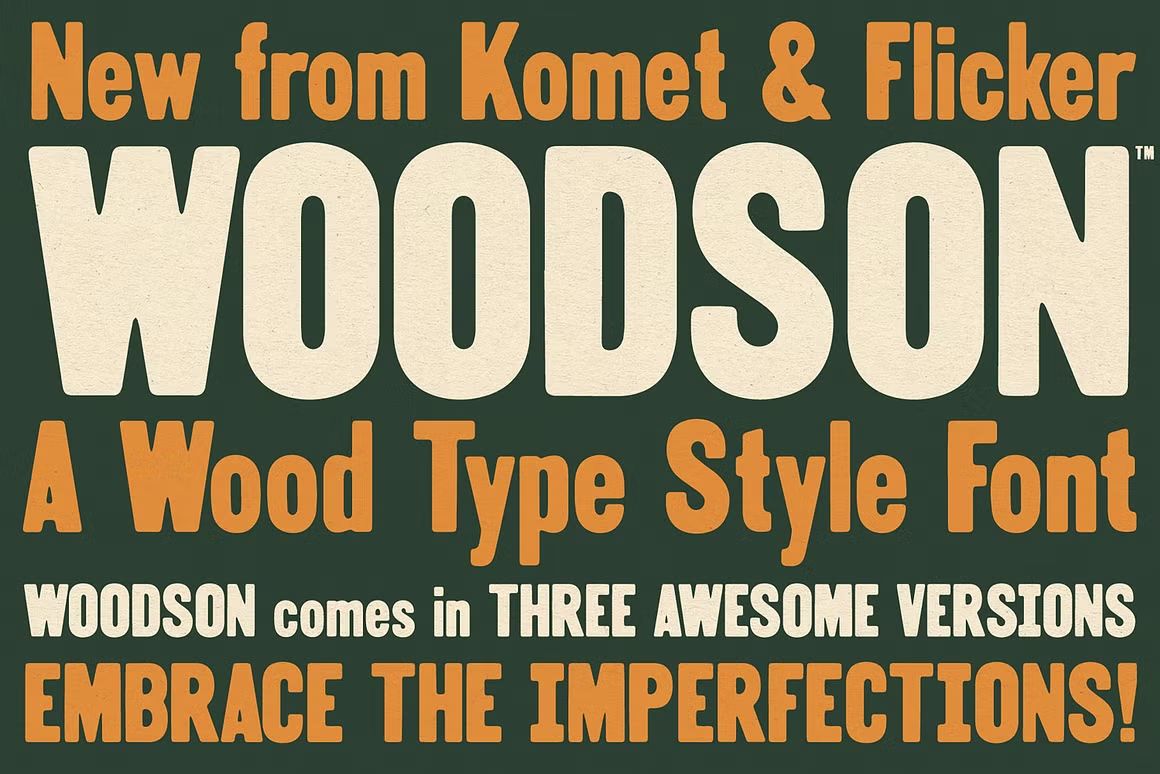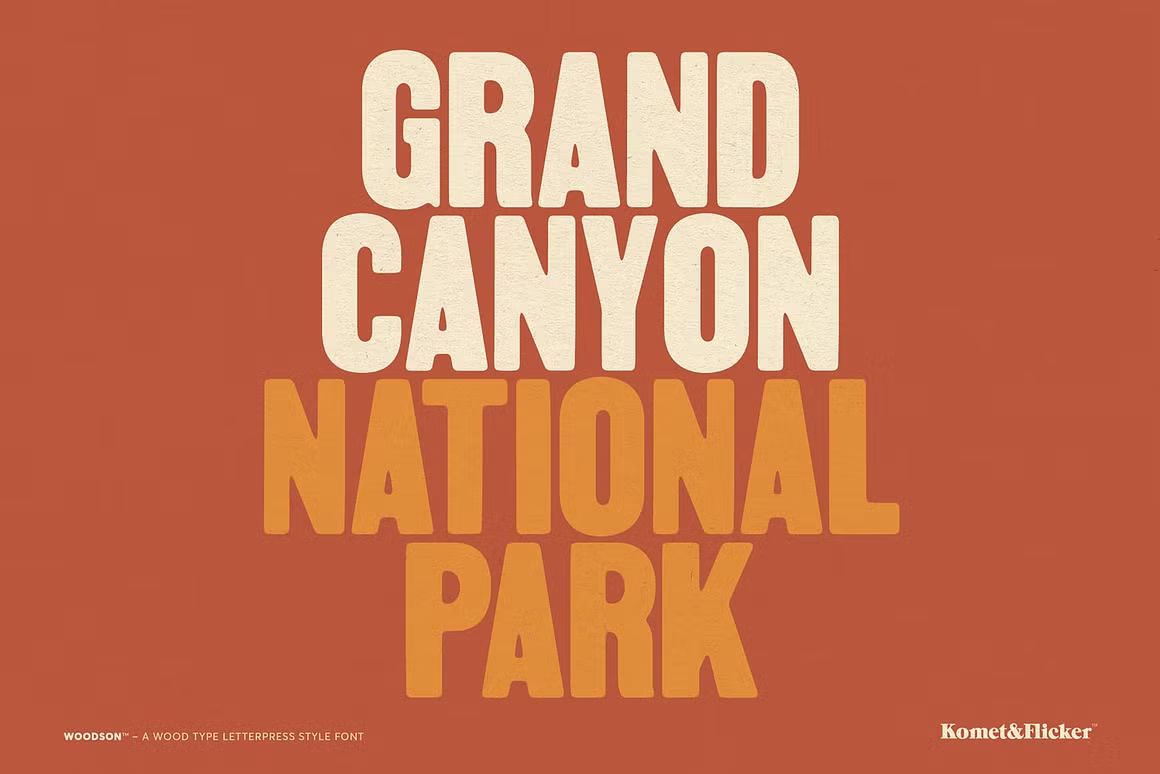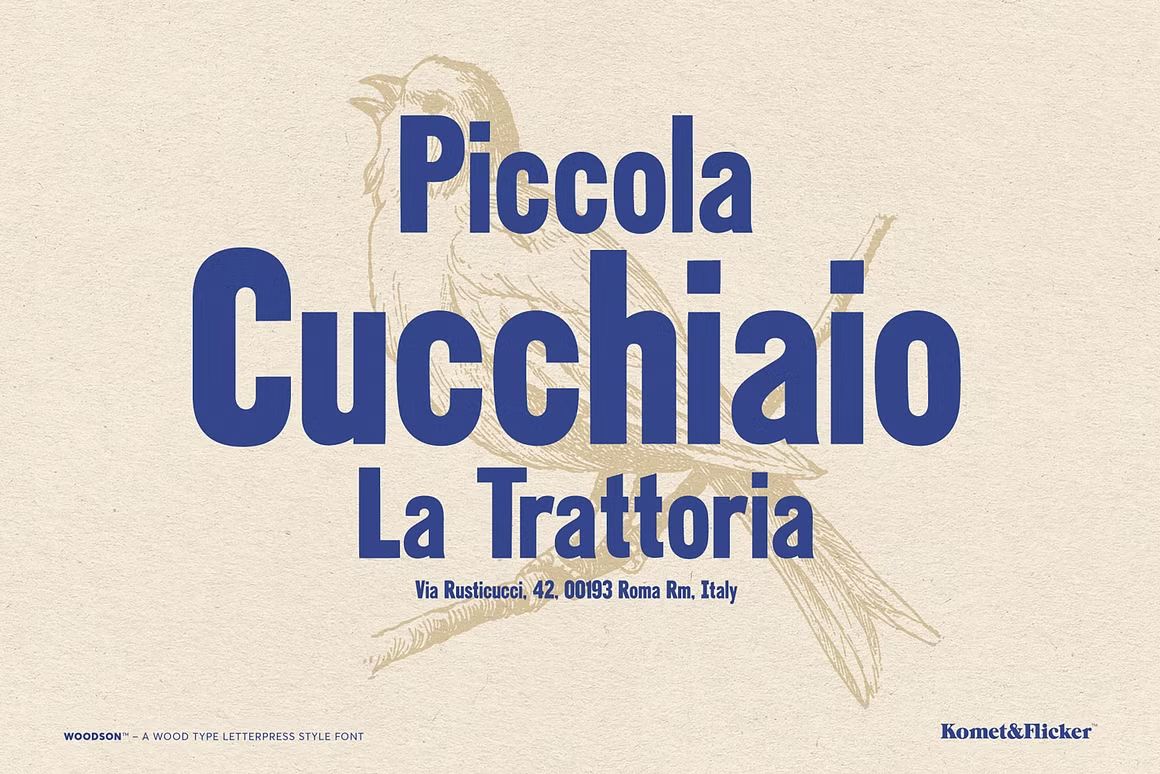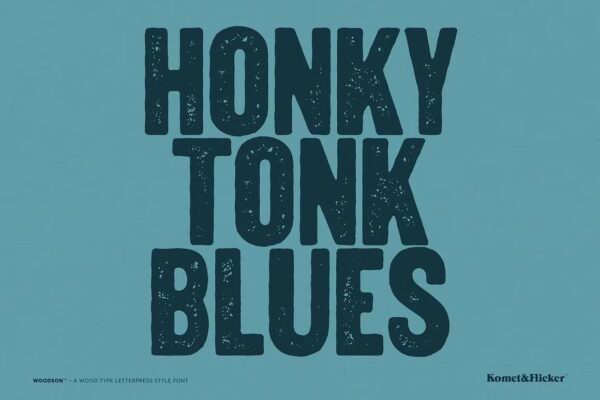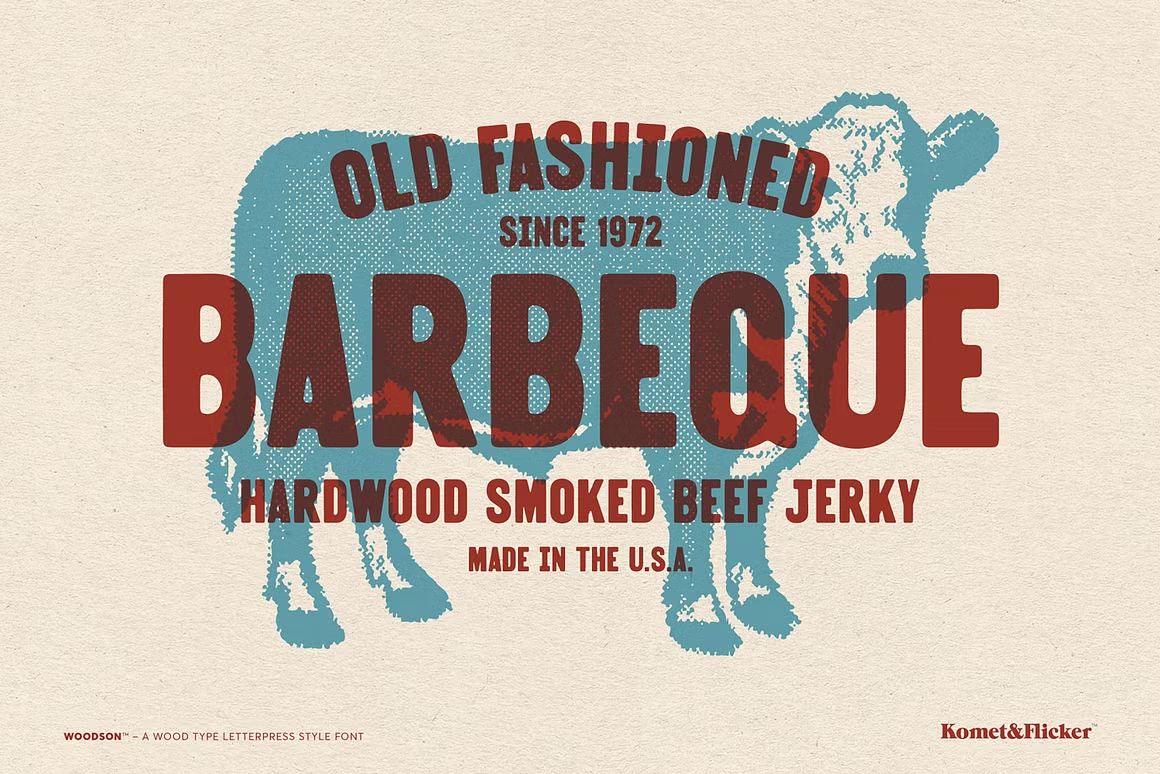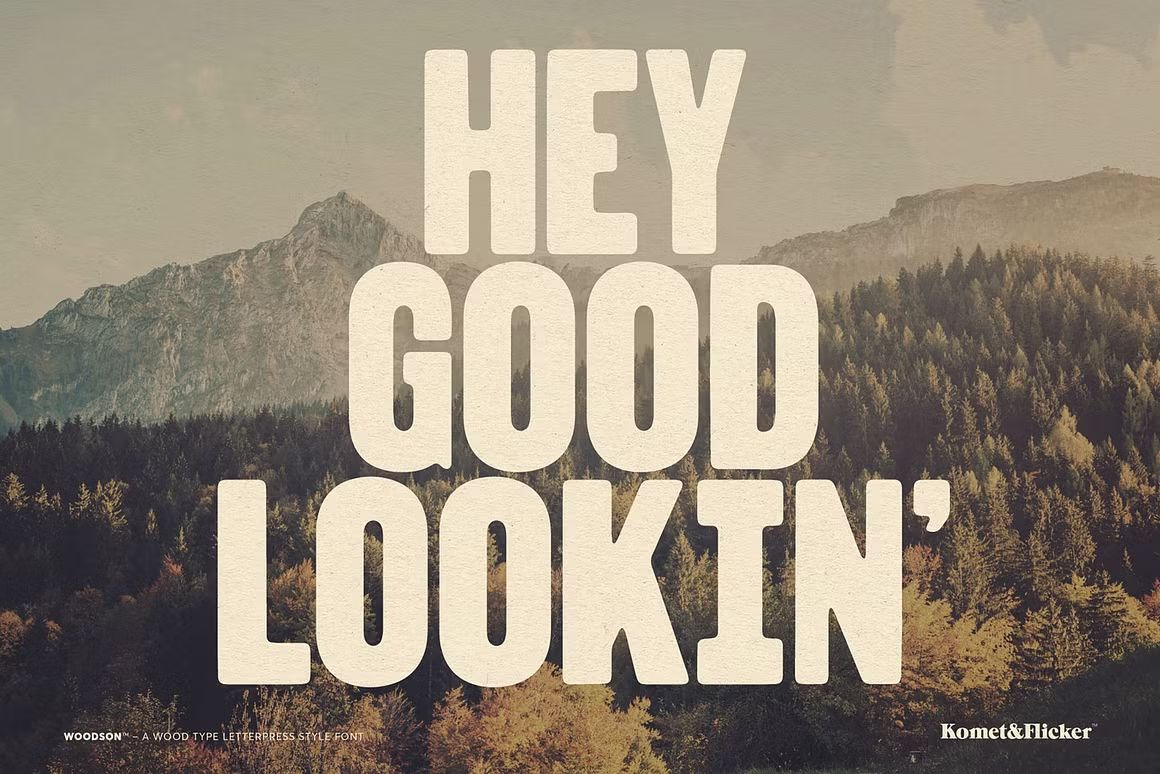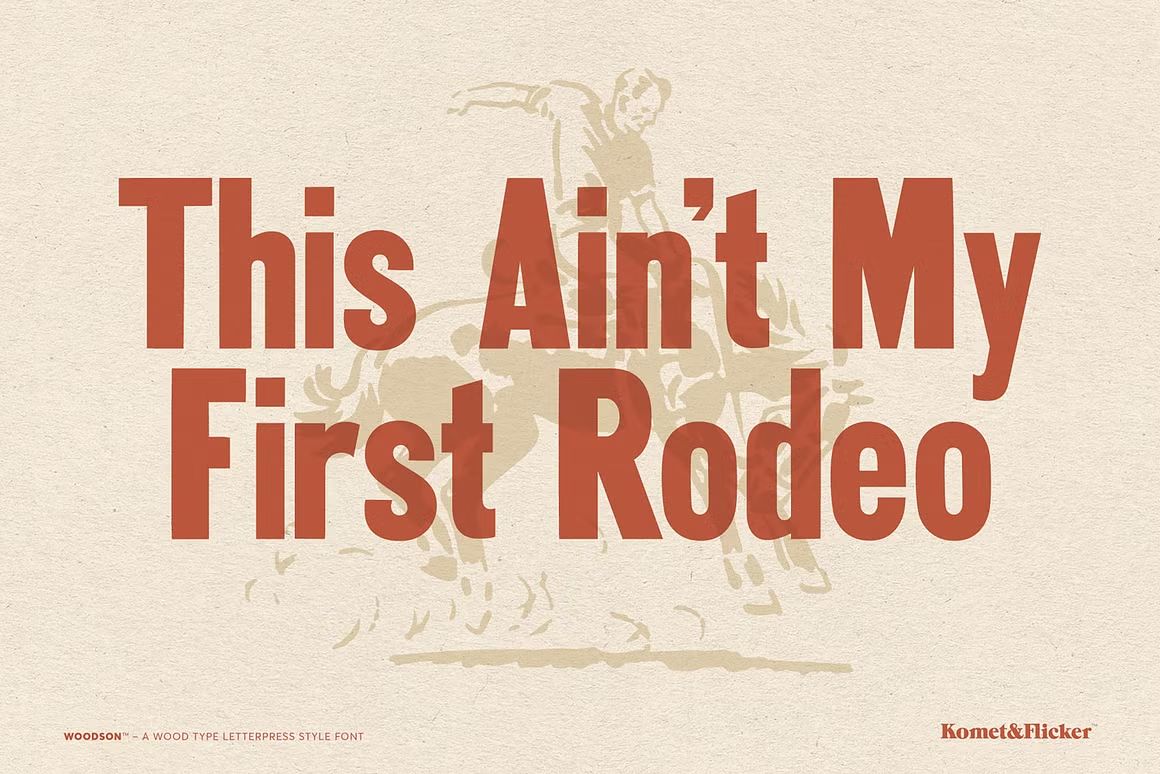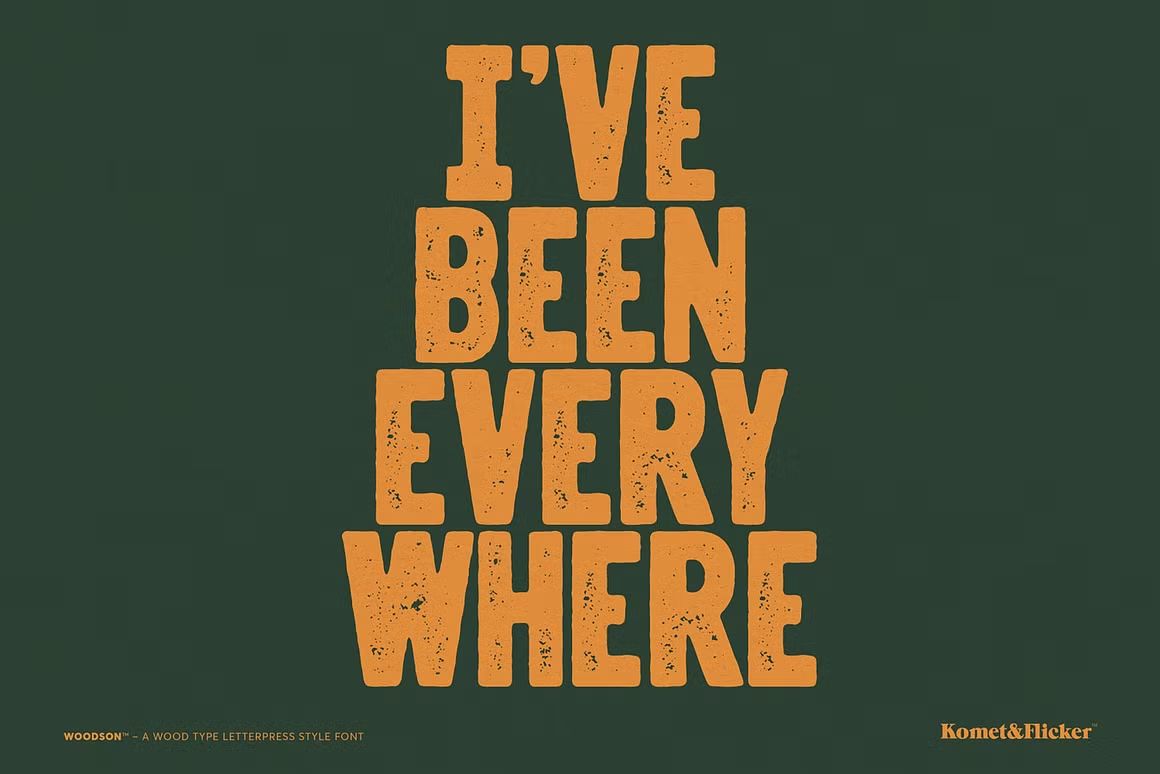
Woodson – Sans Serif Font
Woodson adalah font sans serif modern dan tegas, cocok untuk branding dan desain profesional. Format OTF/TTF/WOFF, siap digunakan di berbagai media.
Woodson adalah font sans serif bergaya modern dengan bentuk huruf yang kuat, bersih, dan serbaguna. Dirancang dengan proporsi seimbang dan garis tegas, font ini cocok untuk branding, editorial, headline, poster, dan tampilan digital. Woodson memadukan kejelasan dan estetika kontemporer, menjadikannya pilihan ideal untuk berbagai proyek desain profesional.
• Gaya sans serif modern yang solid dan mudah dibaca
• Cocok untuk branding, editorial, dan desain digital
• Termasuk huruf kapital, kecil, angka, dan simbol